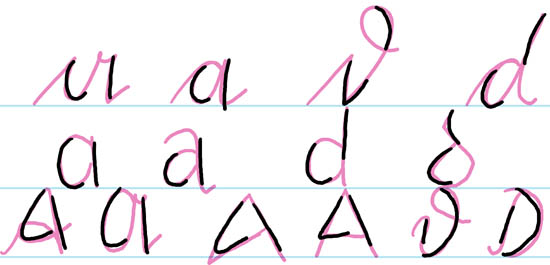
Wann ist ein Buchstabe ein Buchstabe....
Deine Balkengraphik ist ein tolles Beispiel für die Grenzsituation/potentielle Mehrdeutigkeit
Sozusagen eine AHA-Illustration.
Soweit ich das verstanden habe, ging es ja bei der Ehrenrettung für das Sütterlin-h nicht um dessen Funktionalität, sondern um den ehrrührigen Vergleich mit dem Chihuahua.
Aber trotzdem: Dein Vergleich zeigt schön, daß der Unterschied zwischen lateinischem und deutschem h eigentlich nicht bedeutender ist als beispielsweise zwischen den verschiedenen a- und g-Formen innerhalb der Antiqua.
... also, des Chihuahuas Ehrenrettung war, dass er doch ein Hund ist, ebenso wie eine Dogge (nein, das ist wirklich kein Spitz).
Aber mal ganz zum Anfang zurück - Spurensuche nach formalen Zusammenhängen/Gemeinsamkeiten: